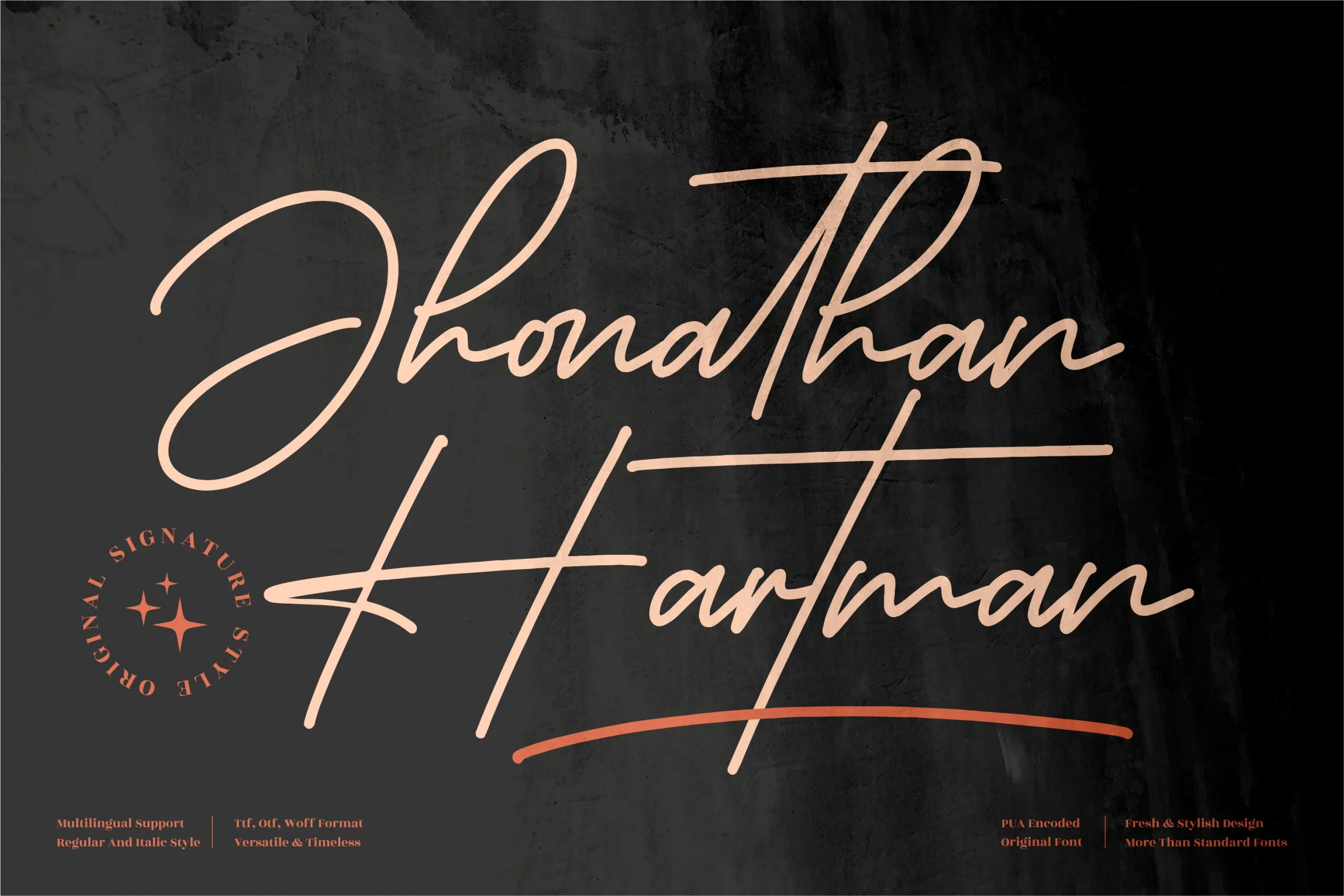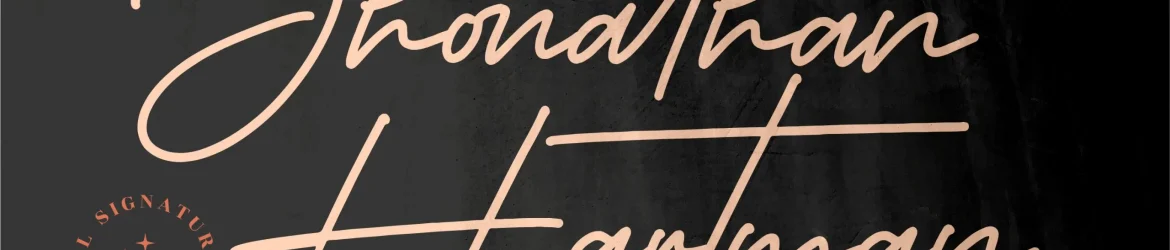
Jhonathan Hartman Font – Download Grátis
A fonte ‘Jhonathan Hartman’ é uma elegante escolha para qualquer projeto que exija um toque sofisticado. Esta monoline signature font foi criada pelo designer perspectype e oferece um gosto premium perfeito para todos os tipos de projetos: desde logotipos e embalagens até invitations, cartões de nome ou etiquetas. Seja qual for o seu projeto, a Jhonathan Hartman é uma escolha sólida que proporcionará qualidade e profissionalismo. Seja ela um quote impresso em mugs para sua cafeteria favorita, a imagem perfeita para sua capa de livro personalizada ou até mesmo a marca final do seu evento especial. A fonte ‘Jhonathan Hartman’ combina com qualquer estilo e permite que você realize seus projetos de forma única, garantindo um toque premium em cada projeto que cria.